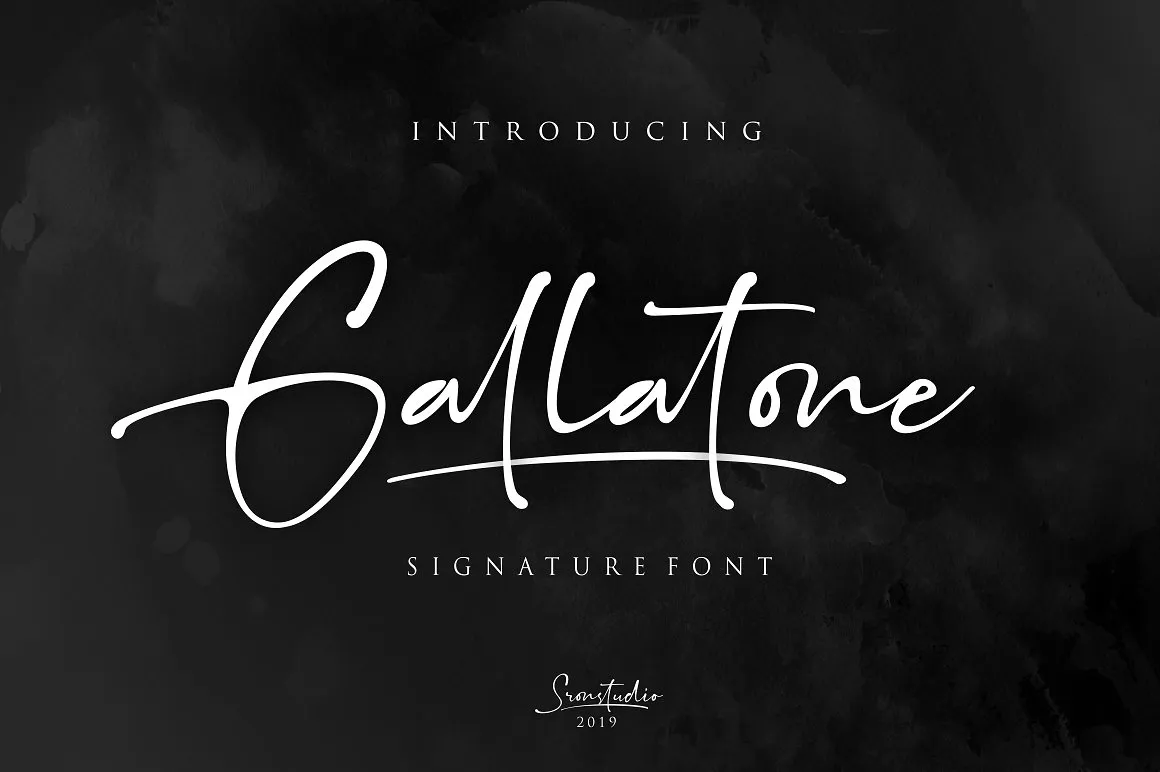
Gallatone Signature Font – Download Grátis
Descubra a elegância e a simplicidade na Galatone Signature Font, uma nova opção para seus projetos digitais. Introduzida pela 0001themes, esta font é perfeita para qualquer marca pessoal ou corporativa que busque um estilo moderno e sofisticado. Com linhas naturais e arquiteturas elegantes, a Galatone foi concebida para fazer deste o ponto de destaque em seu design. Esta font é perfeitamente adequada para uma vasta gama de projetos gráficos, desde logotipos e cartões de convite até embalagens e publicidade. Seja para revolucionar sua identidade visual ou personalizar seus materiais promocionais, a Galatone garante que seja um recurso atemporal em seu portfólio. A Galatone oferece uma opção perfeita para designers profissionais e amadores, pois permite a criação de designs únicos e chamativos. Não importa se você está buscando imprimir mensagens personalizadas em cartões de visita ou se deseja criar um design exclusivo para sua marca online – a Galatone tem tudo o que você precisa. Combinar linhas fluidas com uma aparência minimalista, esta font é perfeita para qualquer tipo de projeto. Seja no ambiente digital ou físico, a Galatone irá destacar seu trabalho e torná-lo único. Seja ele um logotipo inspirador para sua marca online, um cartão de convite sofisticado ou até mesmo uma embalagem elegante – a Galatone tem tudo o que você precisa para seus projetos. Aproveite a oportunidade de adicionar um toque singular e moderno ao seu design com esta font. Descubra por si mesmo o poder da Galatone Signature Font, e revolucione seu projeto de acordo com suas necessidades.